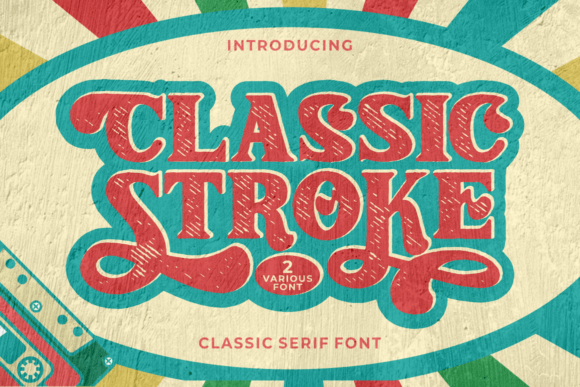
Classic Stroke
Classic Stroke – Revue détaillée du police serif intemporelle
Vous cherchez une police qui allie élégance classique et impact visuel ? Classic Stroke est la réponse idéale. Ce serif bold propose deux déclinaisons (clean et textured) et une multitude de caractères alternatifs, offrant une flexibilité rare pour tous vos projets vintage, rétro ou haut de gamme.
- Style traditionnel inspiré des typographies du XIXe siècle – parfait pour les logos, affiches et packagings au charme d’antan.
- Deux versions distinctes : clean & textured – choisissez la finition qui correspond le mieux à votre identité visuelle.
- Caractères alternatifs multiples – personnalisez chaque mot pour créer des compositions uniques et mémorables.
- Traits épais et lignes nettes – garantissent une lisibilité optimale même à petite taille ou sur écrans haute résolution.
Design et esthétique : Classic Stroke se distingue par ses empattements généreux et ses contrastes forts, rappelant les polices de presse d’époque tout en restant résolument modernes. La version textured ajoute une légère usure qui renforce le côté « vintage », idéale pour les projets qui veulent évoquer le passé sans paraître datés.
Polyvalence d’usage : Que vous créiez une identité de marque vintage, un flyer rétro ou une publication Instagram au look « old school », cette police s’adapte immédiatement. Les caractères alternatifs permettent de jouer sur la hiérarchie typographique sans recourir à plusieurs polices différentes.
Verdict : La police incontournable pour un look rétro‑chic
En résumé, Classic Stroke combine authenticité classique et flexibilité créative. Sa disponibilité en version clean ou textured, ainsi que ses nombreux caractères alternatifs, en font un atout précieux pour les designers cherchant à renforcer l’impact visuel de leurs projets tout en conservant une esthétique intemporelle. N’attendez plus, intégrez Classic Stroke à votre boîte à outils et donnez à vos créations le caractère élégant et distinctif qu’elles méritent.